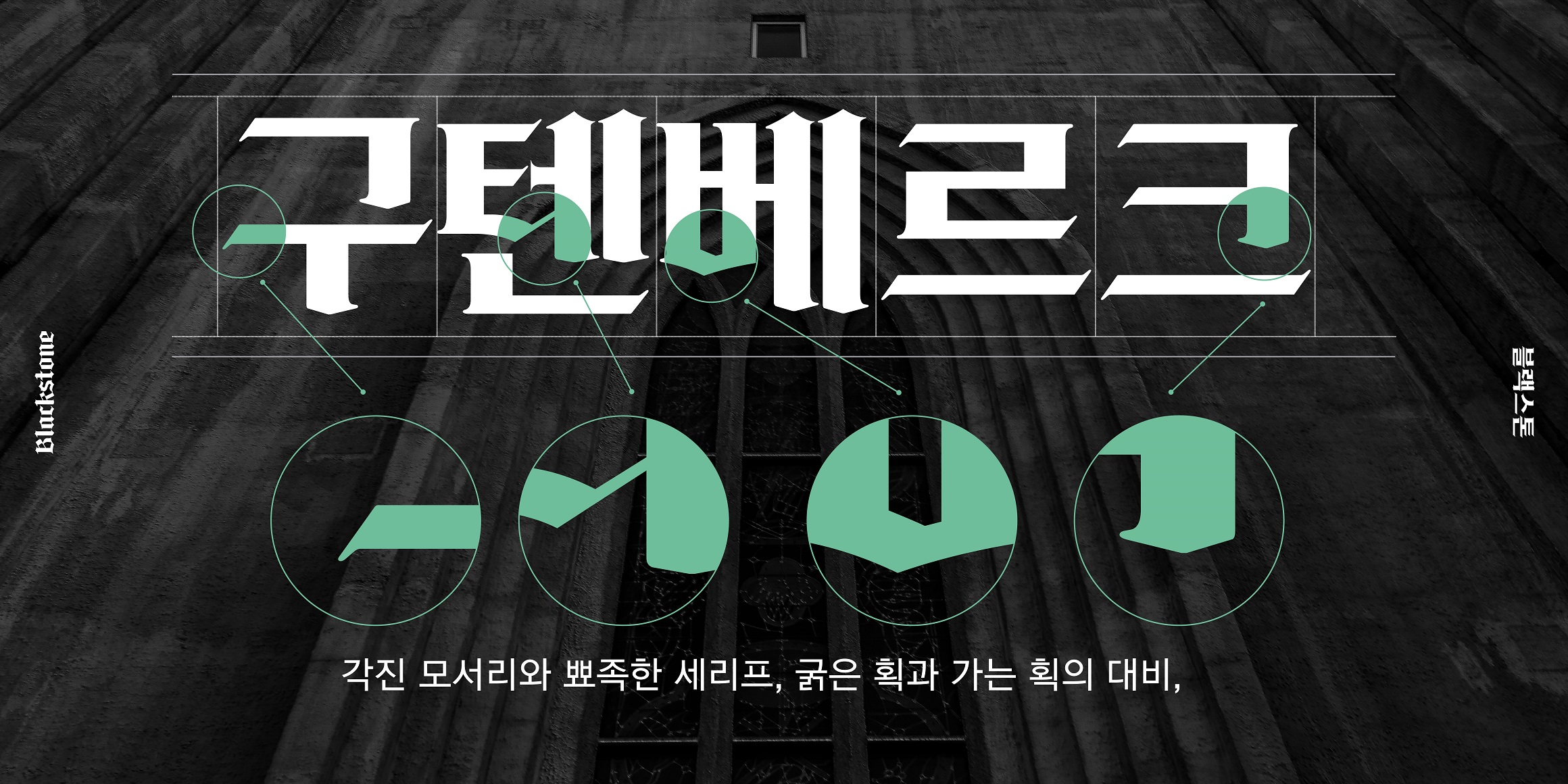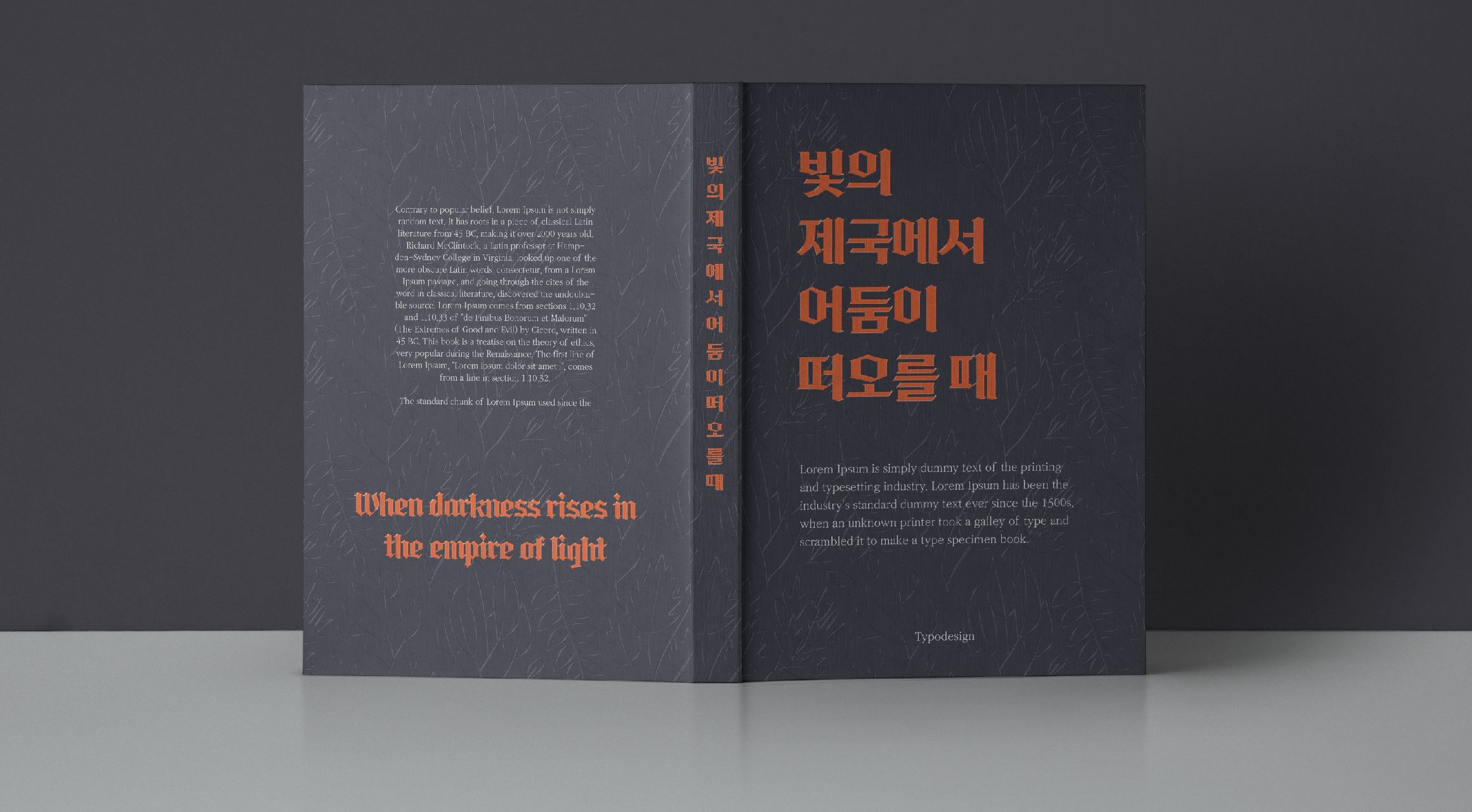
타이포_블랙스톤
『직지심체요절』의 발견 전까지 세계최초의 금속활자로 알려졌던 구텐베르크의 42행 성서에 사용된 글자체로 알려진 블랙레터에서 영감을 받아 블랙스톤을 개발하였습니다. 블랙레터는 형태에 따라 Textura, Rotunda, Schwabacher, Fraktur, 등이 있는데, 블랙스톤은 이 블랙레터의 성격을 종합하여 디자인하였습니다. 그 중에서 Textura의 성격이 가장 강해 각진 모서리와 뾰족한 세리프, 굵은 획과 가는 획의 대비, 직선과 곡선의 조화 등이 특징입니다. 특징적인 요소를 많이 가지고 있는 폰트라 사람들에게 강한 인상을 줄 수 있는 폰트입니다. 그렇기 때문에 미스터리나 판타지 소설의 제목, 젊은 거리의 간판 등에 사용한다면 시각적으로 임팩트를 줄 수 있습니다. 독일이나 프랑스 등 유럽감성의 브랜드 패키지나 로고 등에 추천 드립니다.
타이포_블랙스톤